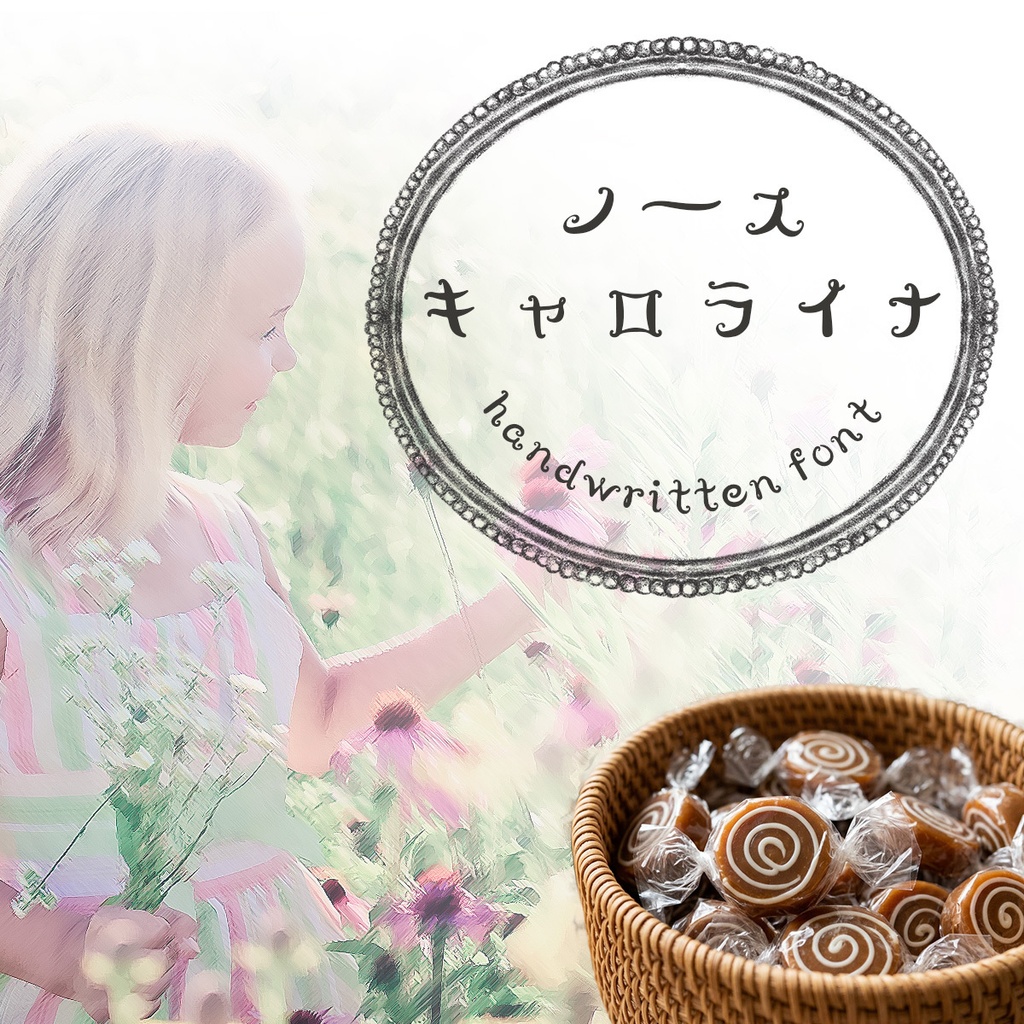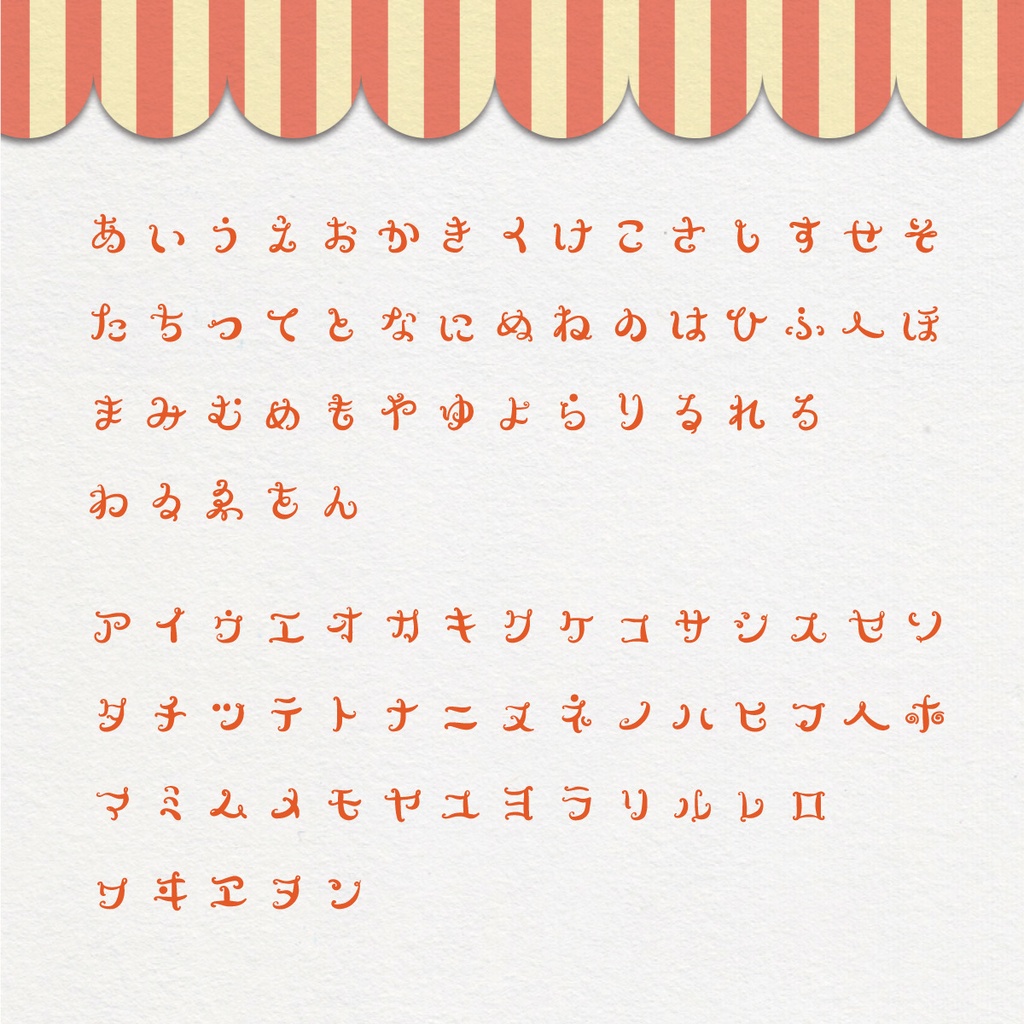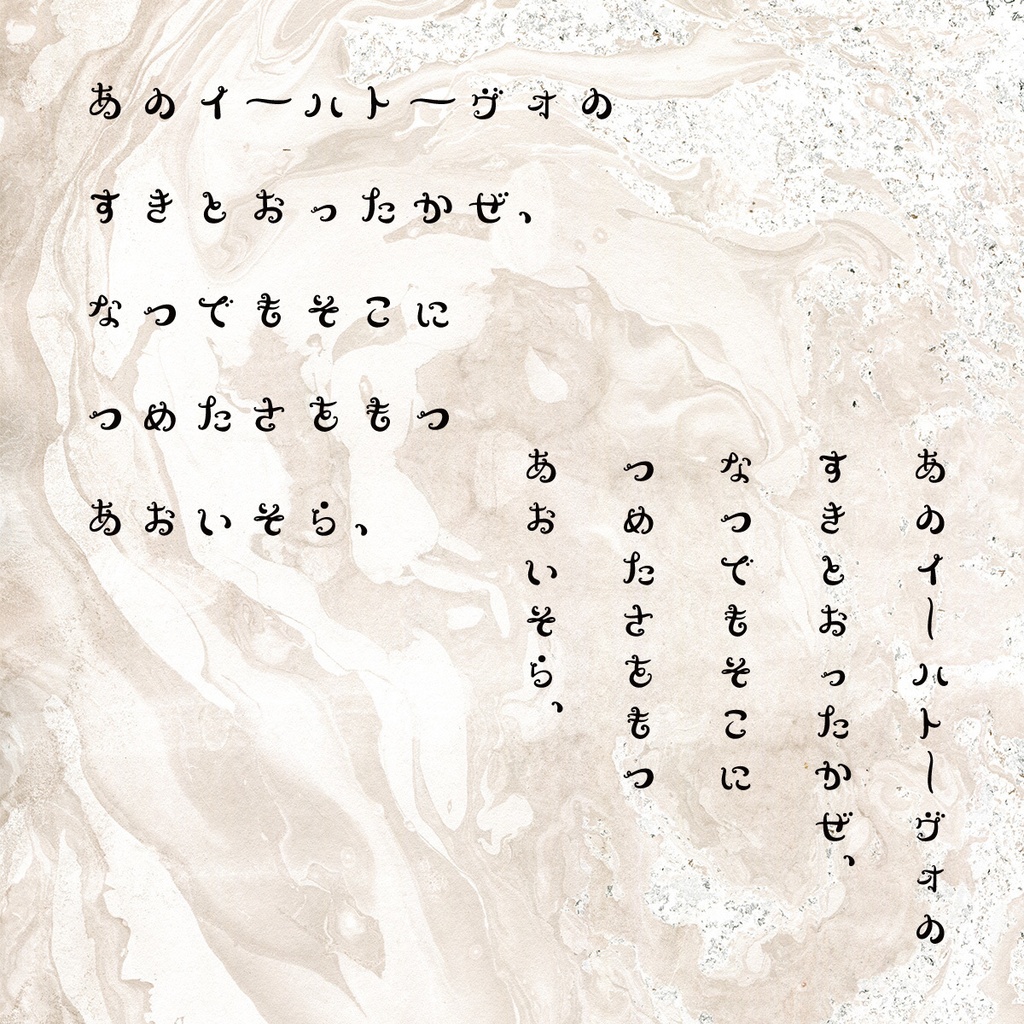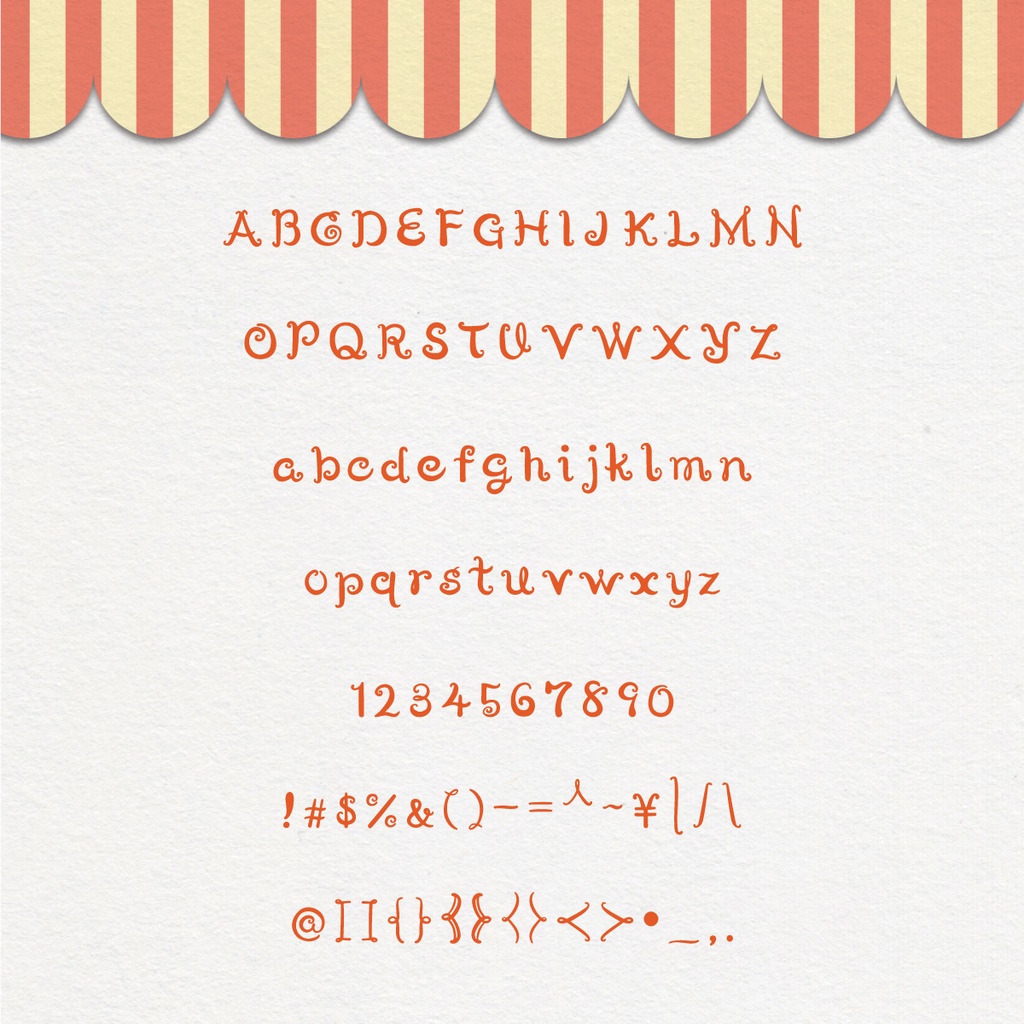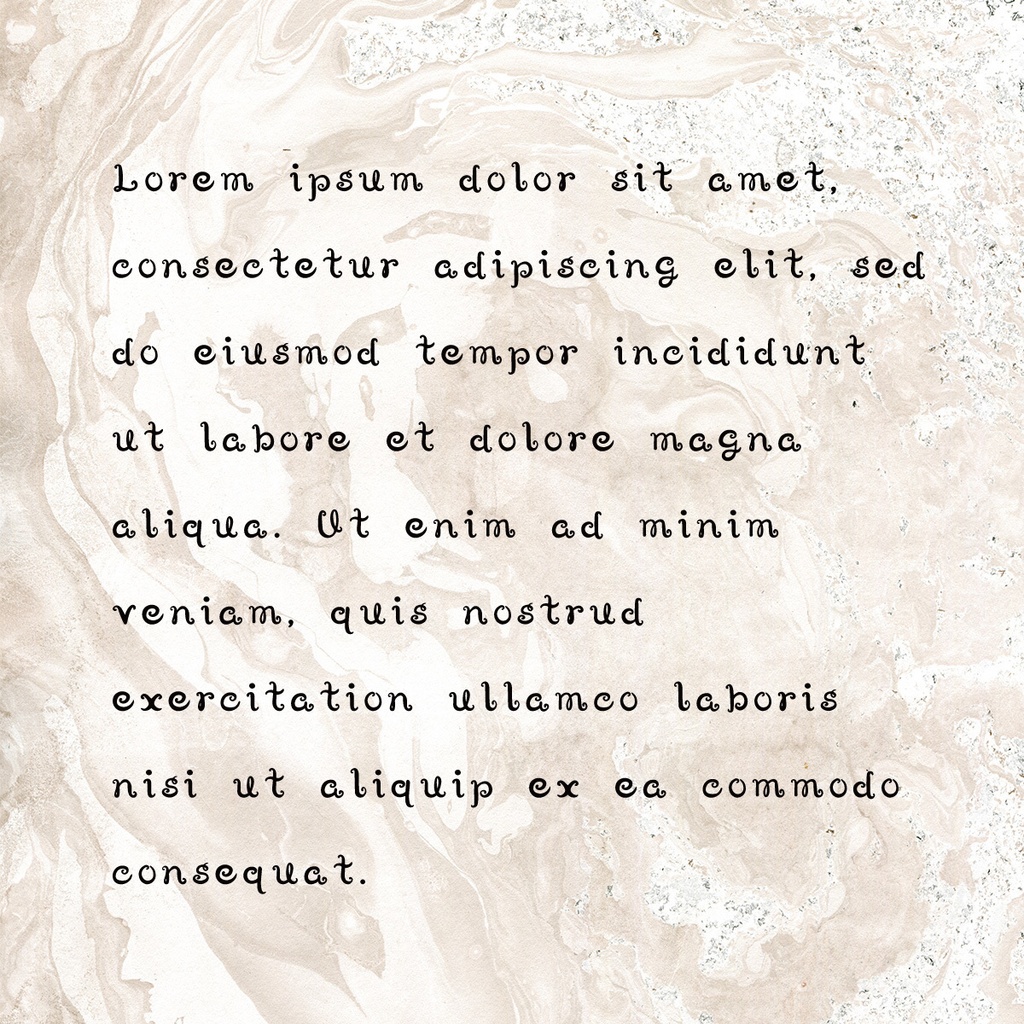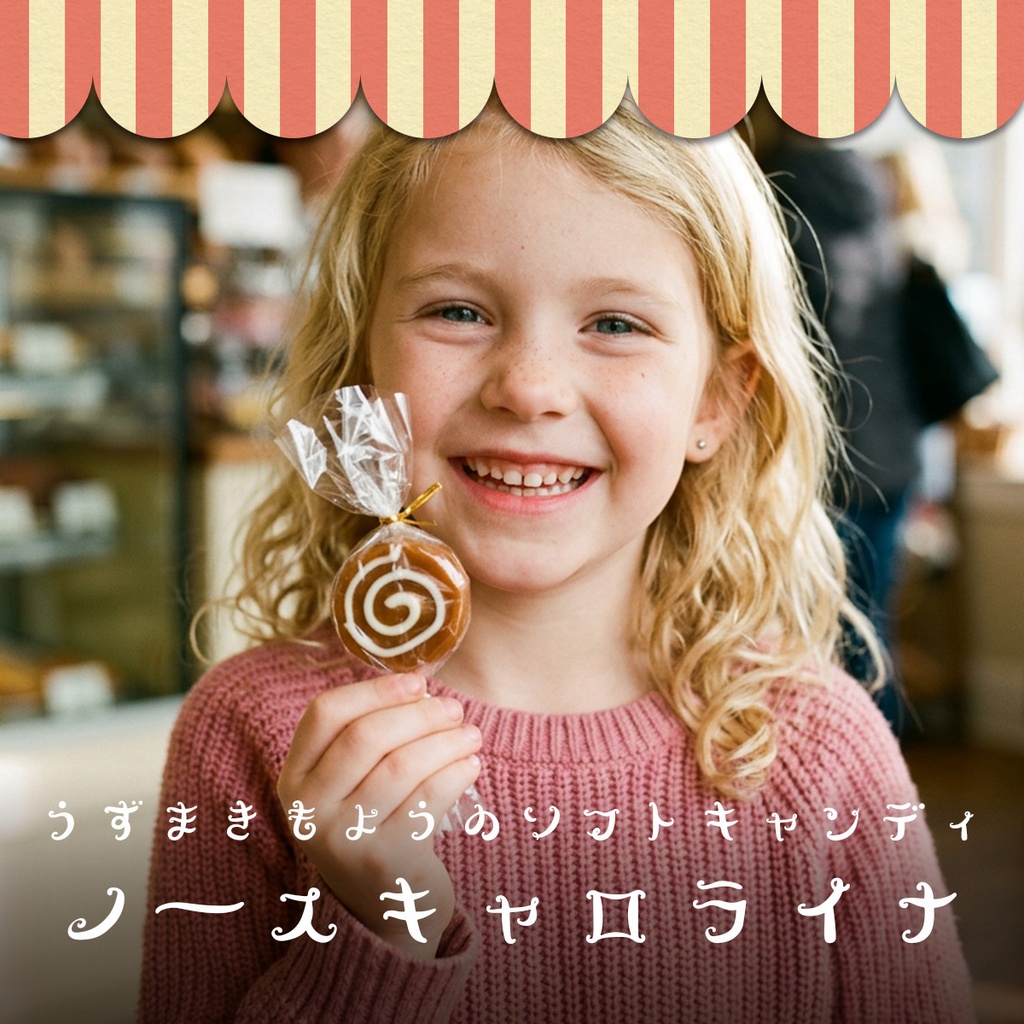
【商用可・縦書き対応】オリジナル手書きデコラティブフォント | North Carolina ひらがな・カタカナ版
【商用可・縦書き対応】オリジナル手書きデコラティブフォント | North Carolina ひらがな・カタカナ版 なつかしの不二家「ノースキャロライナ」をイメージしたフォント
手書きデコラティブフォント | ノースキャロライナ(ひらがな・カタカナ版)
なつかしの不二家「ノースキャロライナ」をイメージして作りました。 くるくるカーブがかわいく優雅な印象。 すこしノスタルジック、でも新しい、そしておしゃれなフォントに仕上げました。 【商用可・縦書き対応】 同人誌・SNS・動画・WEBデザインなど幅広い用途にお使いいただけます。 商用利用OKです。 ひらがな・カタカナ・アルファベット・記号 収録 フォント形式:OpenTypeフォント 【動作環境】Windows / Mac 対応 【インストール方法】 Windows:ダウンロードしたZIPを解凍し、.otfファイルを右クリック→「インストール」 Mac:Font Bookにファイルをドラッグ&ドロップ ▼ まず試してみたい方へ ・無料お試し版(英数字・記号のみ)→ https://vanillabeanz.booth.pm/items/2907297 【ご利用条件について】 ・個人・商用利用ともにご利用可能です。 ・ご利用にあたってクレジット表記の必要はありません。 ・フォントの著作権は、放棄しておりません。 ・ご使用によるトラブルや損害等、一切の責任を負いませんのでご了承ください。 下記の事項でご利用いただけます。 1. WEB・印刷物・動画へのデザインに使用 2. ソーシャルメディア、電子書籍への使用 3. ロゴへの使用(商標登録は不可) (※ご不明な場合は、お問い合わせください。) 4.LINEスタンプへの使用 ※イラスト等のセリフへの使用可能 フォントがメインキャラクターにならない場合のみ使用可能です。 下記の事項でのご利用は不可とさせていただきます。 1. フォントデータの販売 2. フォントデータの再配布 3. 商標登録 4. 公序良俗に反するものへの利用